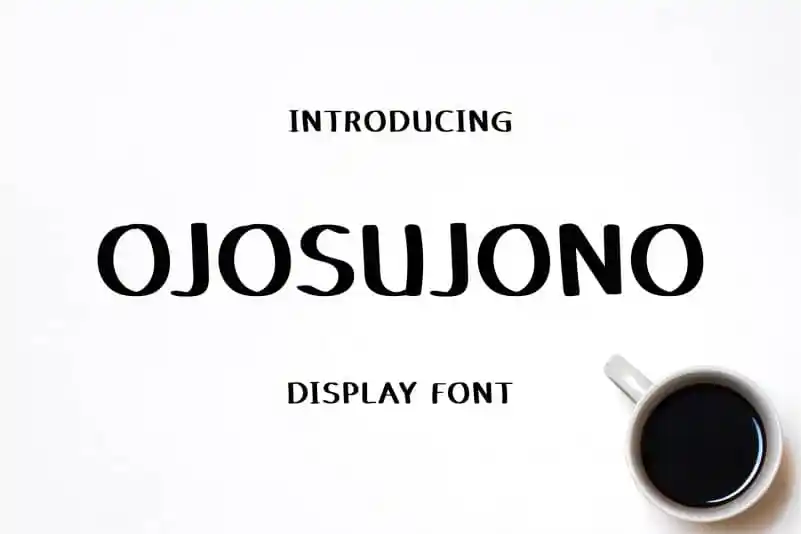
Ojosujono Display Font – Fonte Grátis
Ojosujono Display Font
A fonte ‘Ojosujono Display Font’ é uma delícia para os olhos com seu estilo de escrita à mão relaxado e amigável. Ideal tanto para projetos de marca, cabeçalhos quanto para designs de casamentos, convites ou assinaturas, essa fonte eleva qualquer trabalho ao nível mais alto. Com um toque leve e descontraído, ‘Ojosujono Display Font’ se destaca como uma opção perfeita para designers que buscam uma identidade visual única e agradável. Suas linhas sutis e harmoniosas permitem criar designs profissionais sem perder o charme pessoal, tornando-a uma escolha ideal não apenas para projetos de design gráfico, mas também para criações em geral. Perfeito para diferentes tipos de uso, essa fonte é uma excelente adição ao seu arsenal de recursos gráficos. Seja você um designer de marca, criador de conteúdo online ou até mesmo um artista pessoal, a ‘Ojosujono Display Font’ estará sempre pronta para ajudar a dar vida à sua ideia única e personalizada.